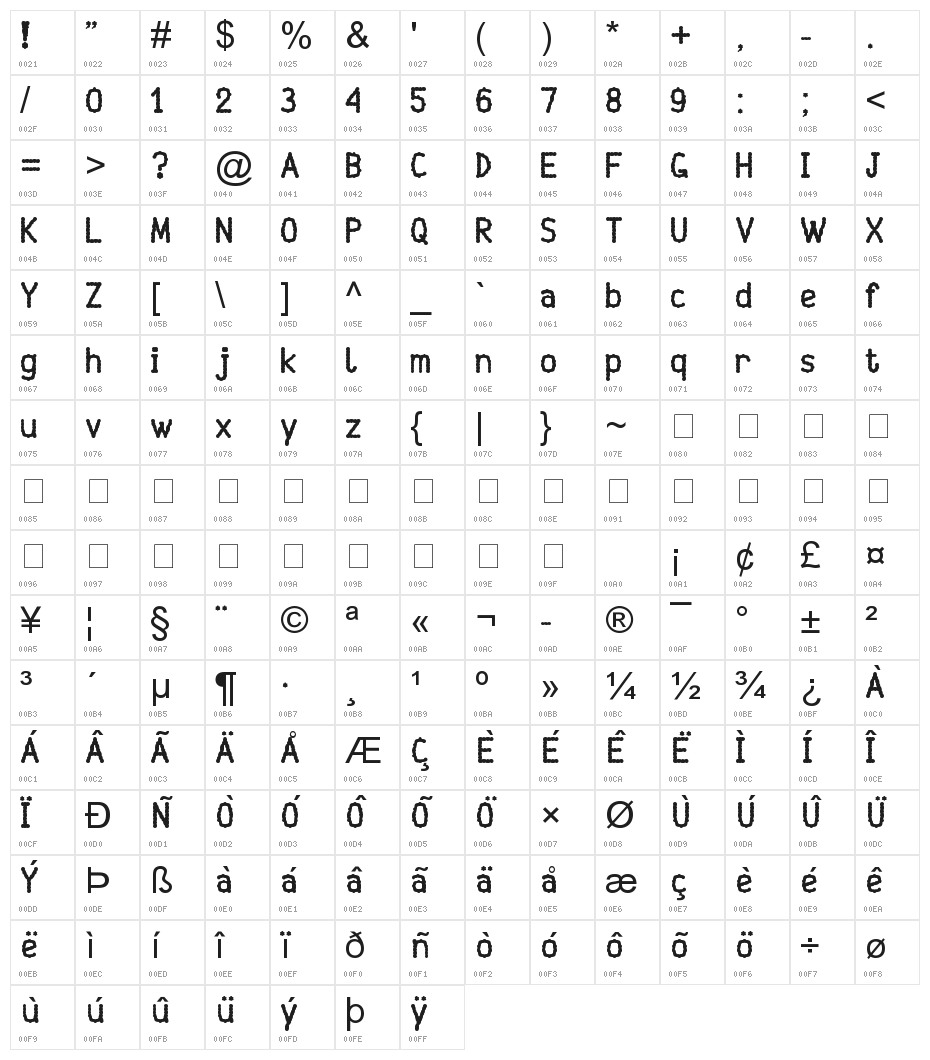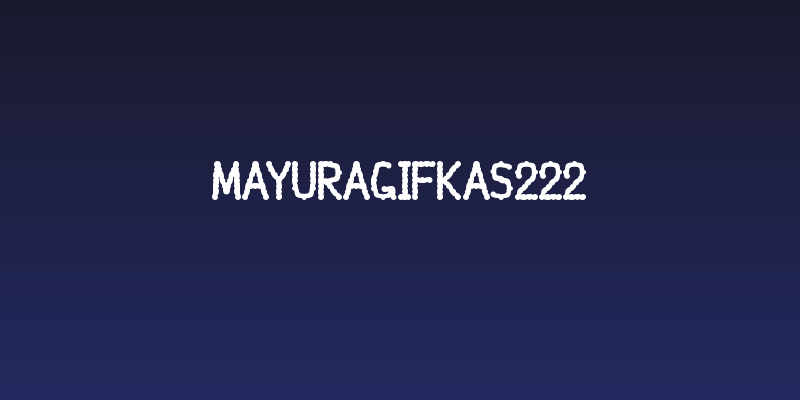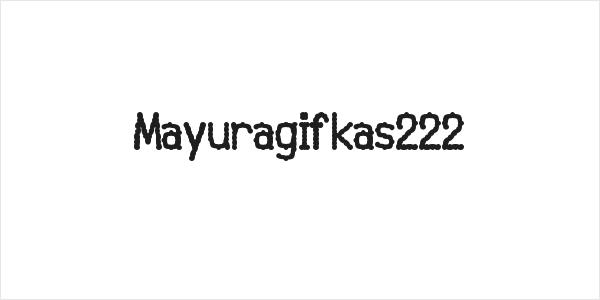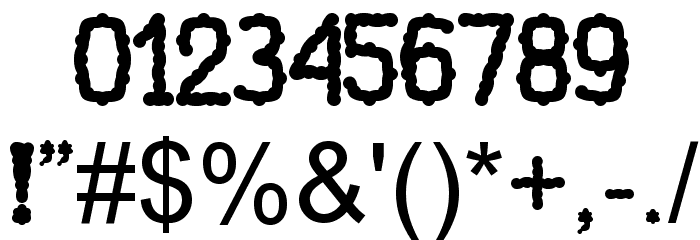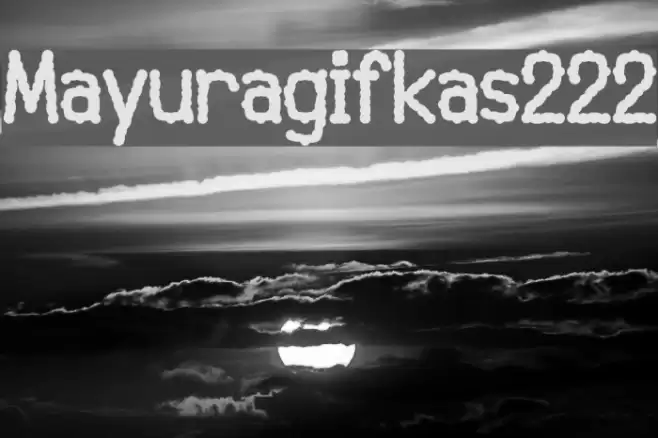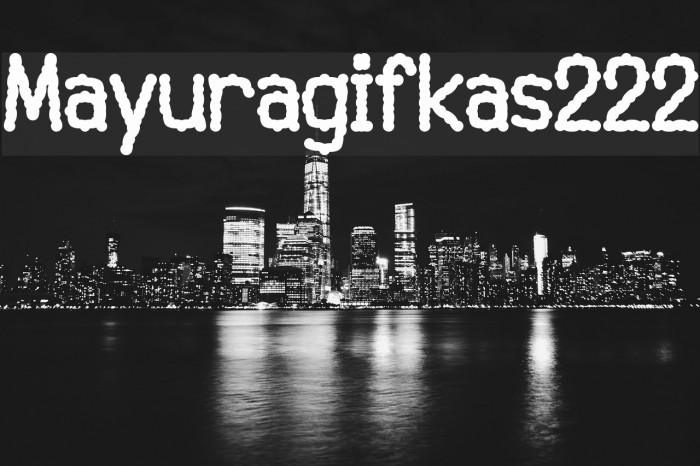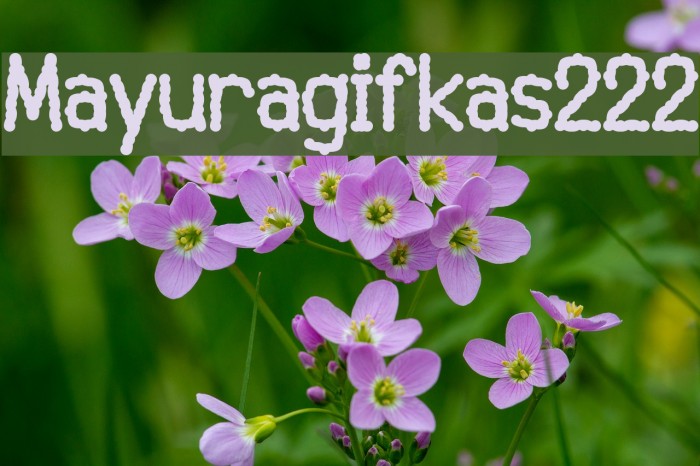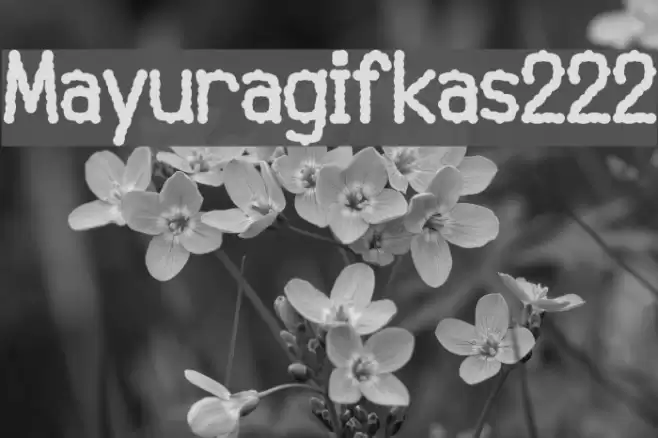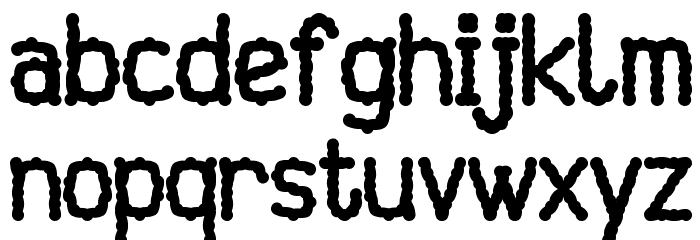
Mayuragifkas222 Font
| Estilo general | Playful, Whimsical |
| Proyectos propuestos | Ideal for children's books, party invitations, playful branding, and creative posters. |